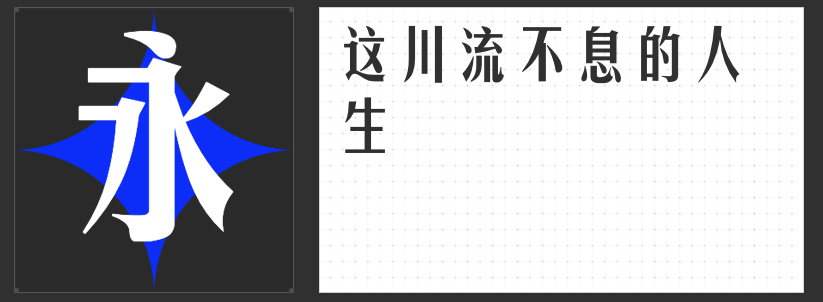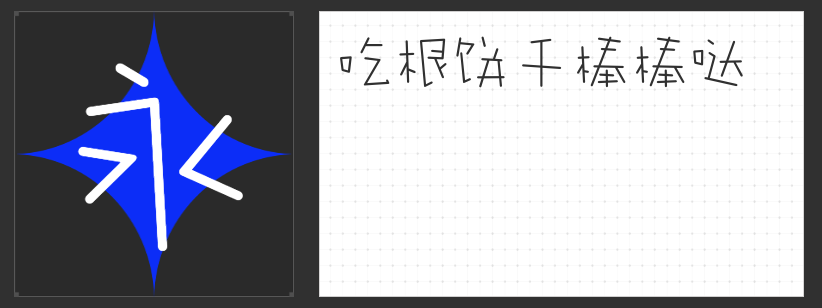
印刷设计中的个性之选:四款风格迥异的字库字体推荐
在印刷设计的世界里,字体不仅是文字的载体,更是视觉语言的重要组成部分。一款合适的字体,能够瞬间提升设计的格调与氛围。今天,我们将为您推荐四款独具特色的字库字体,它们各具魅力,定能为您的印刷作品增添无限可能。
这款字体以其无拘无束的设计风格脱颖而出。它的笔画分布与结构仿佛随意挥洒,却又巧妙地组合成一个个圆润可爱的字形,如同用饼干棒拼凑出的奇妙世界。这种打破常规的笔顺与结构,赋予了字体一种无厘头的幽默感,非常适合用于需要营造轻松、活泼氛围的印刷设计。
这款字体以其完美的斜度与利索的转折,展现出一种独特的个性魅力。它摒弃了过度的装饰,转而通过棱角分明的线条来传达力量与决心。全直线的设计不仅符合当代视觉审美,更在视觉上降低了阅读障碍,为读者提供了舒适的阅读体验。在需要强调力量感与现代感的印刷设计中,它无疑是绝佳的选择。
三、励字综艺简繁
这款字体以其粗犷的笔画与方正的拐弯处理,展现出一种活泼而严谨的艺术气质。它尽量将空间充满,使得每个字形都显得饱满而有力。同时,圆润的拐弯处理又为其增添了几分柔和与亲切感。这款字体非常适合用于需要兼具艺术性与实用性的印刷设计。
四、励字美黑简
这款字体巧妙地融合了黑体与宋体的优点,既保留了黑体的匀称与力量感,又融入了宋体的清秀与美观。它给人以端正、正气的视觉效果,非常适合用于需要传达正式、权威信息的印刷设计。
这四款字体各具特色,无论您是需要营造轻松氛围,还是强调力量感,亦或是追求艺术性与实用性的平衡,都能在其中找到满意的选择。